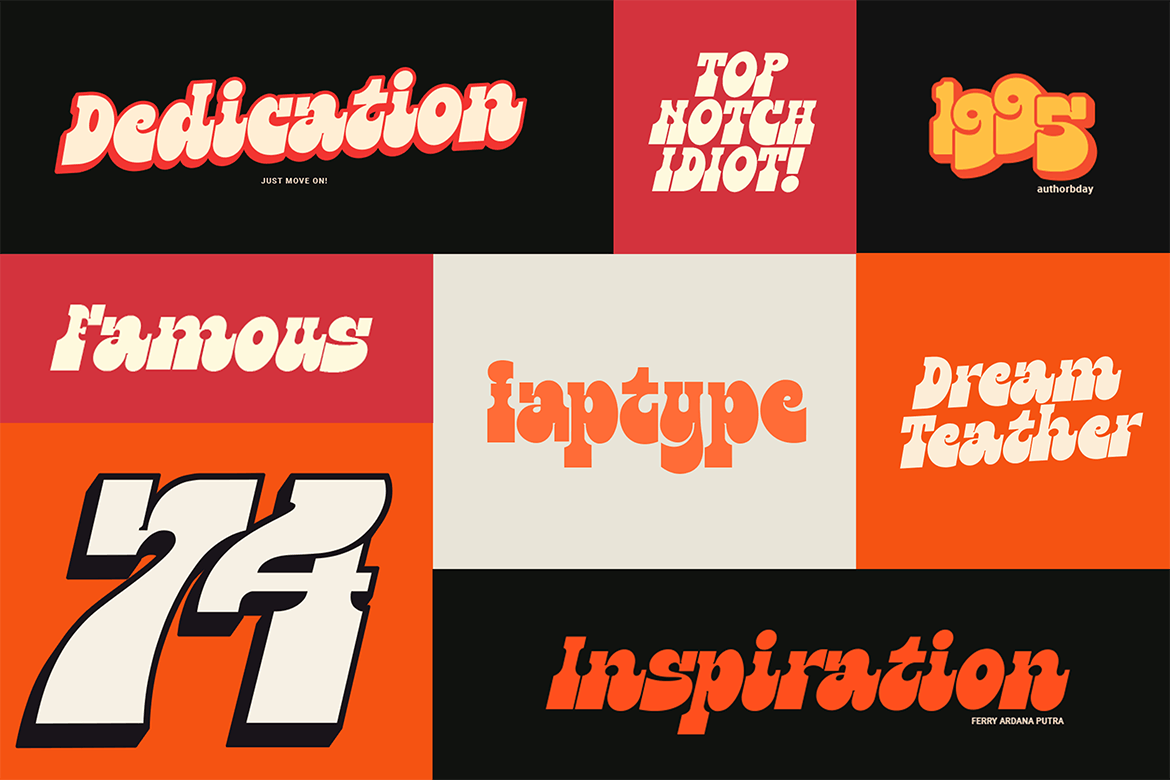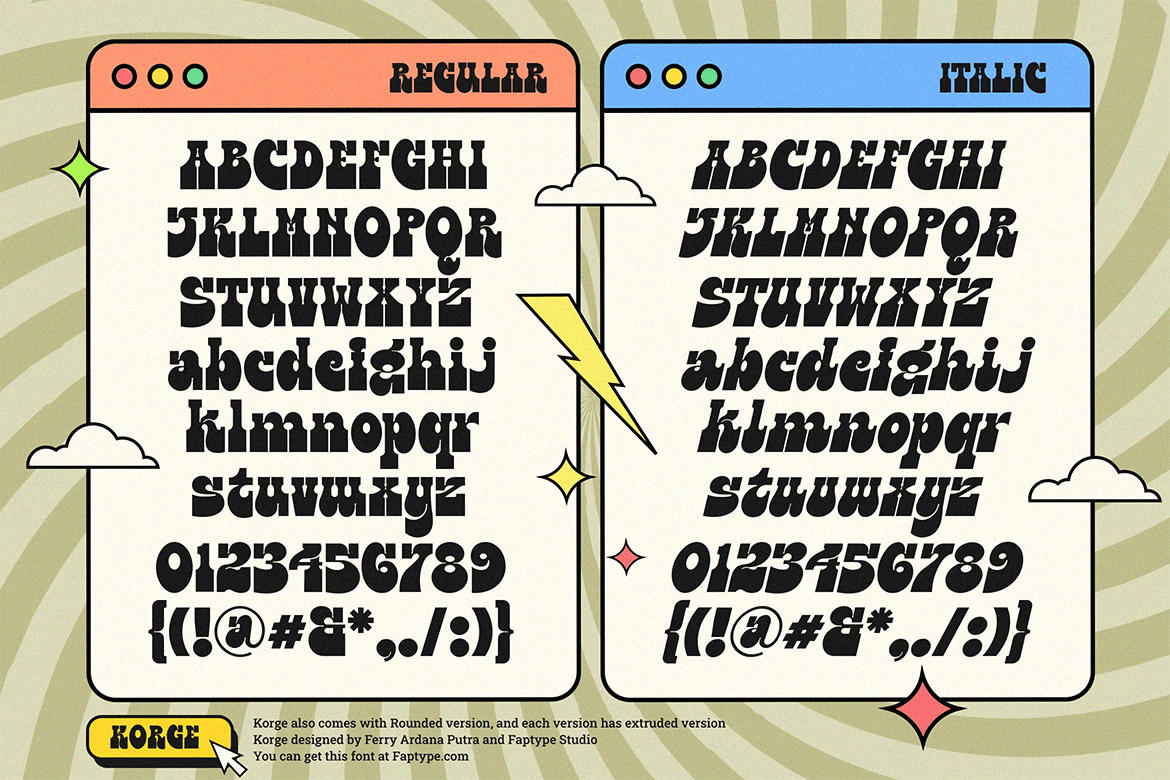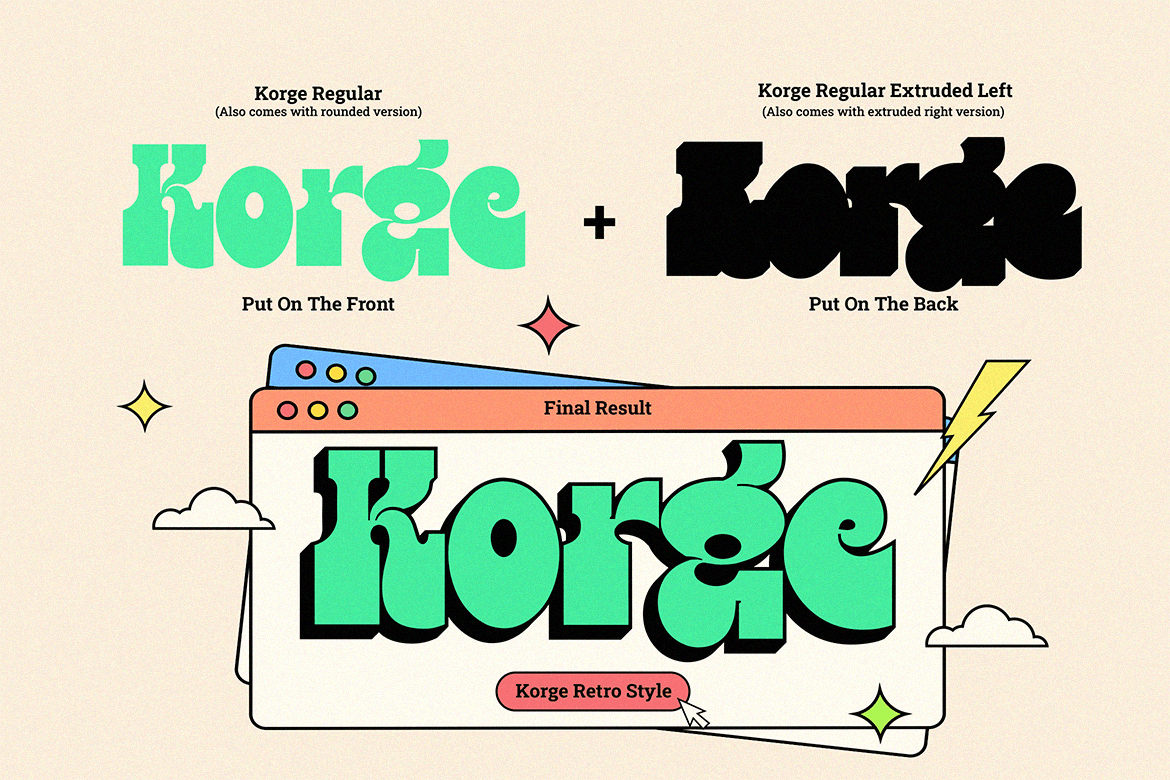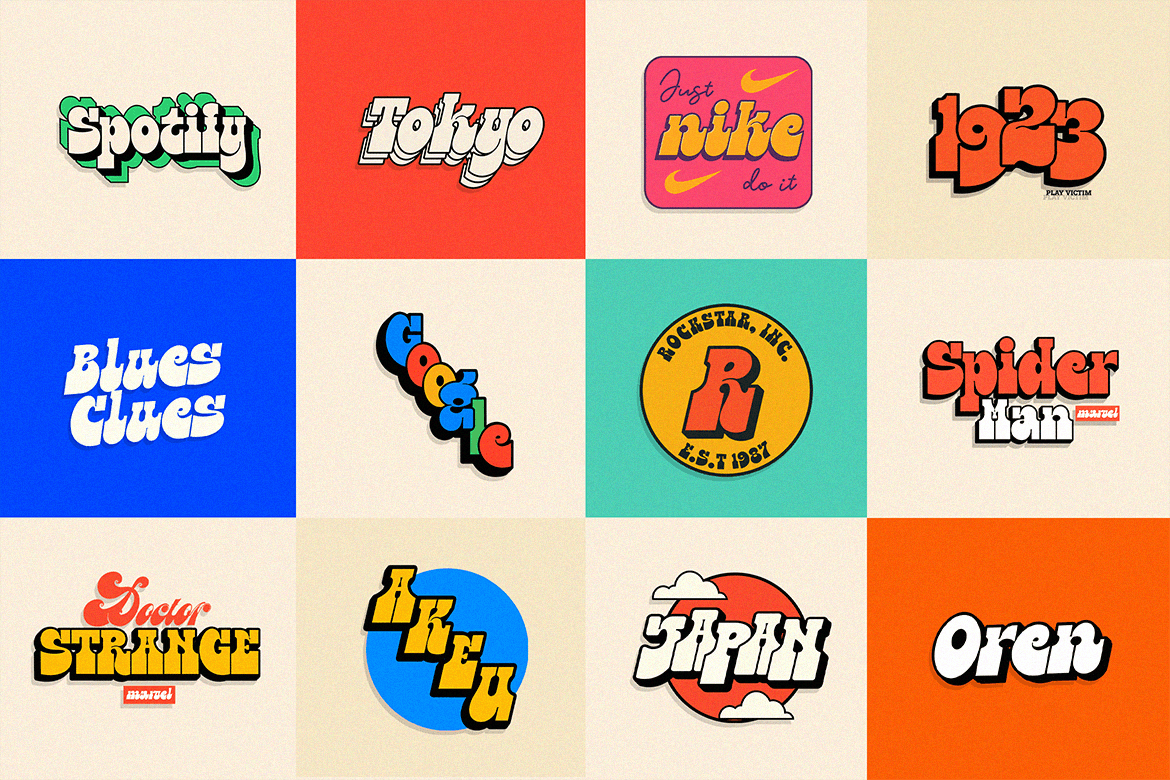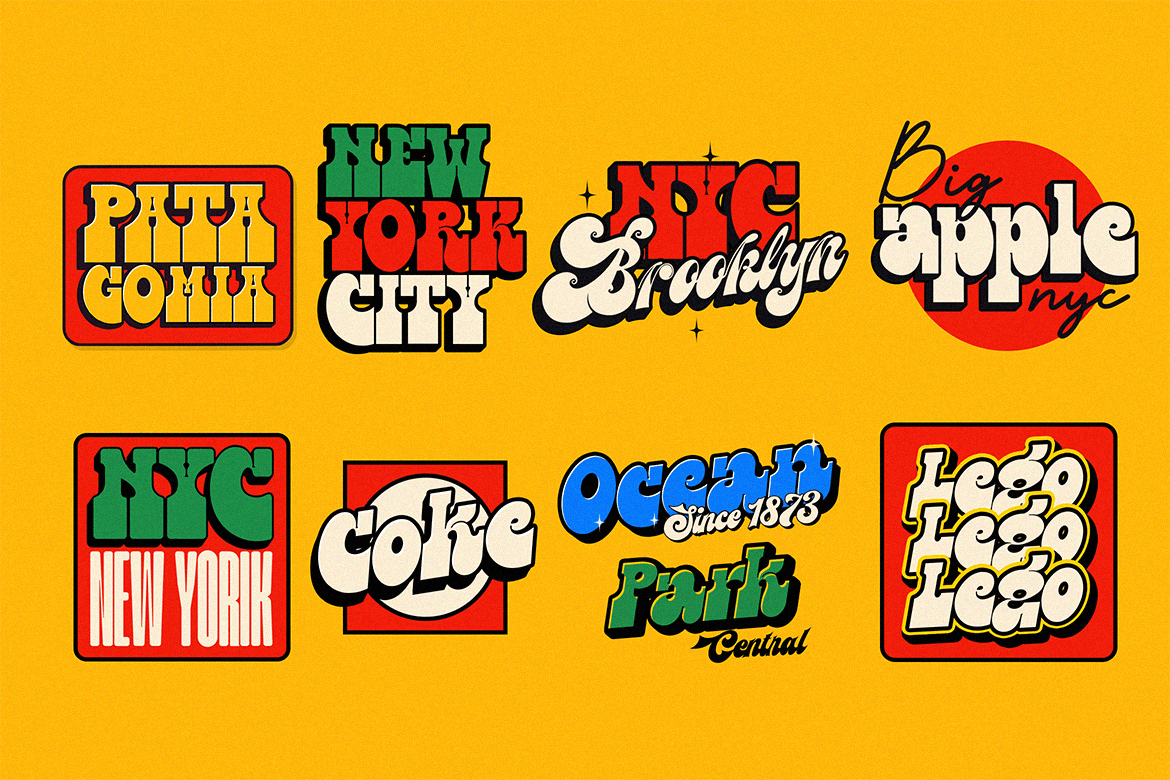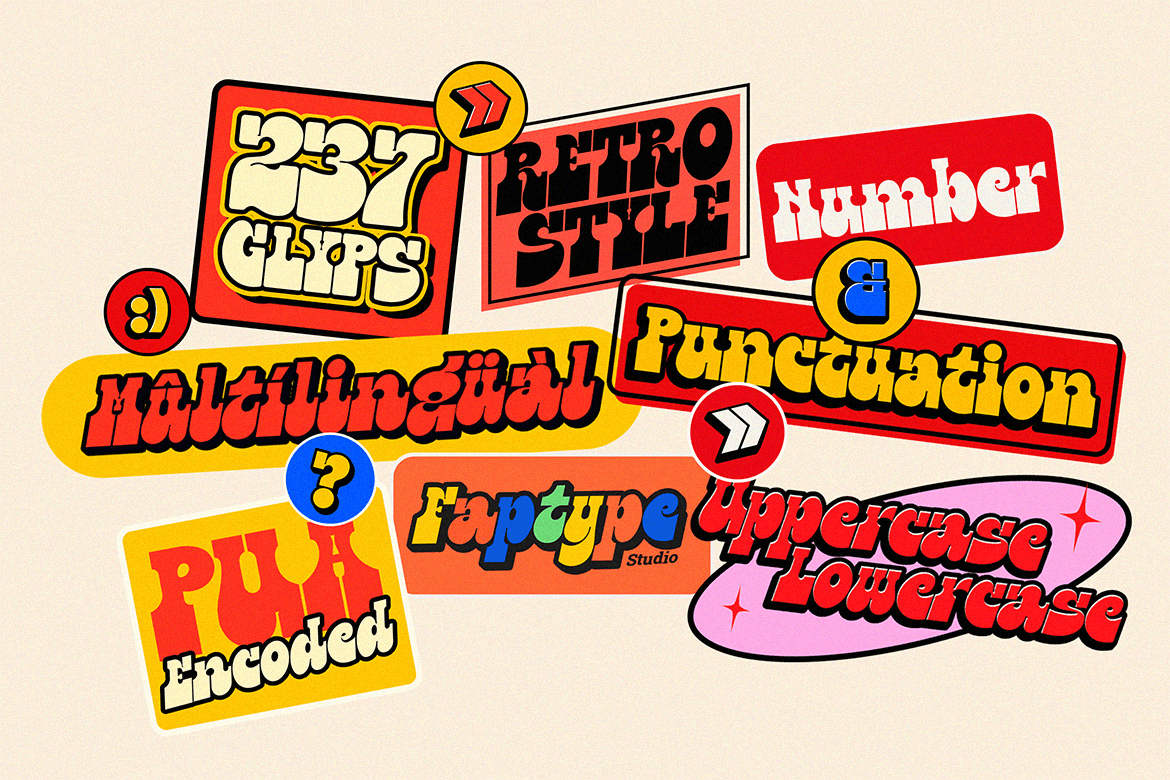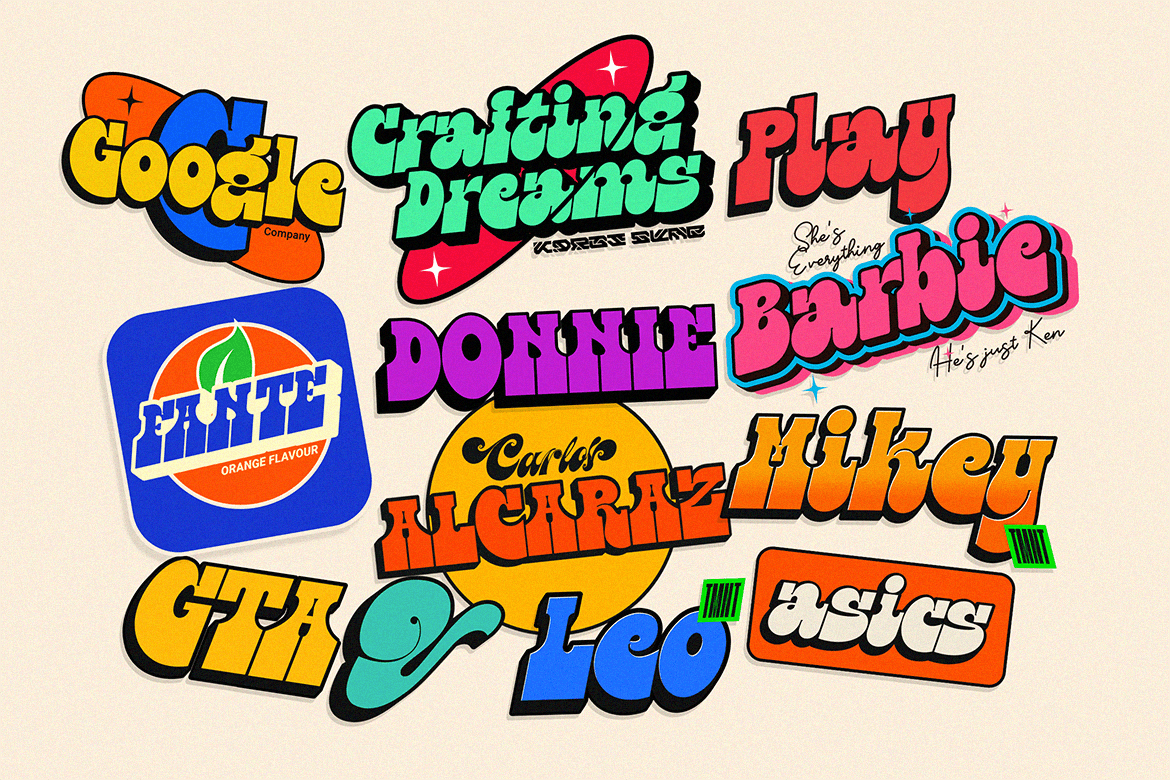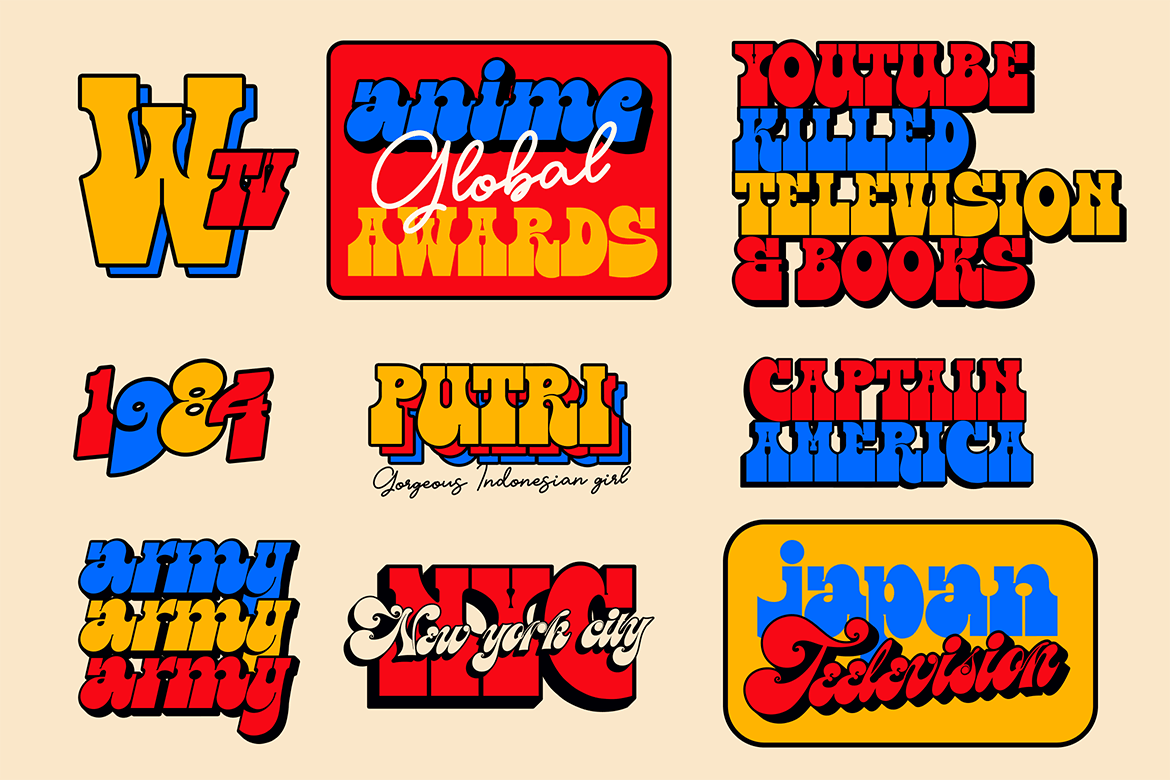
معرفی "Korge"، یک فونت جذاب و چندکاره با طراحی Bold Slab Serif که زیباییهای نوستالژیک را با کارایی مدرن ترکیب میکند. با طراحی جسورانه، فرم سریف و سه نسخه متفاوت شامل عادی، گرد و برجسته، Korge امکانات خلاقانه زیادی را برای پروژههای طراحی شما فراهم میآورد.
Korge فونتی است که پروژههای شما را به دوران طلایی طراحی میبرد. سریفهای جسور و متمایز آن حس نوستالژیا را تداعی میکنند و به آثار شما جذابیت کلاسیک و ماندگاری میبخشند.
Korge سه سبک متمایز برای انتخاب دارد. نسخه عادی حضوری قدرتمند دارد، در حالی که نسخه گرد لبهها را نرمتر کرده و حس نزدیکتری ایجاد میکند. نسخه برجسته عمق و بعد را اضافه میکند و به متن شما کیفیت سهبعدی و چشمنواز میبخشد.
Korge زبان طراحی را بدون مرز صحبت میکند. با پشتیبانی از چندین زبان و کدگذاری PUA، اطمینان حاصل میکند که پیام شما با مخاطبان از پسزمینههای زبانی متنوع ارتباط برقرار کند.
از طراحی لوگو تا برندینگ، بستهبندی، پوسترها و فراتر از آن، Korge به راحتی با انواع پروژههای طراحی سازگار میشود. سریفهای جسور این فونت توجه را به خود جلب میکند و اطمینان میدهد که پیام شما با قدرت و سبک منتقل میشود.
Korge شما را به یک سفر خلاقانه دعوت میکند. عناوین به یاد ماندنی، لوگوهای نمادین یا تابلوهای چشمگیر بسازید – این فونت بوم شما برای فراتر رفتن از مرزهای طراحی است.
با Korge، امکانات بیپایان است. طراحی Bold Slab Serif الهام گرفته از سبک نوستالژیک، پشتیبانی از چند زبان و سبکهای چندمنظوره آن را به انتخاب ایدهآلی برای طراحانی تبدیل میکند که میخواهند پروژههای خود را با جذابیتهای بیزمان و مدرن تزریق کنند. آماده شوید تا با Korge، جایی که کلاسیک با مدرن ملاقات میکند، دیدگاههای خود را به واقعیت تبدیل کنید.